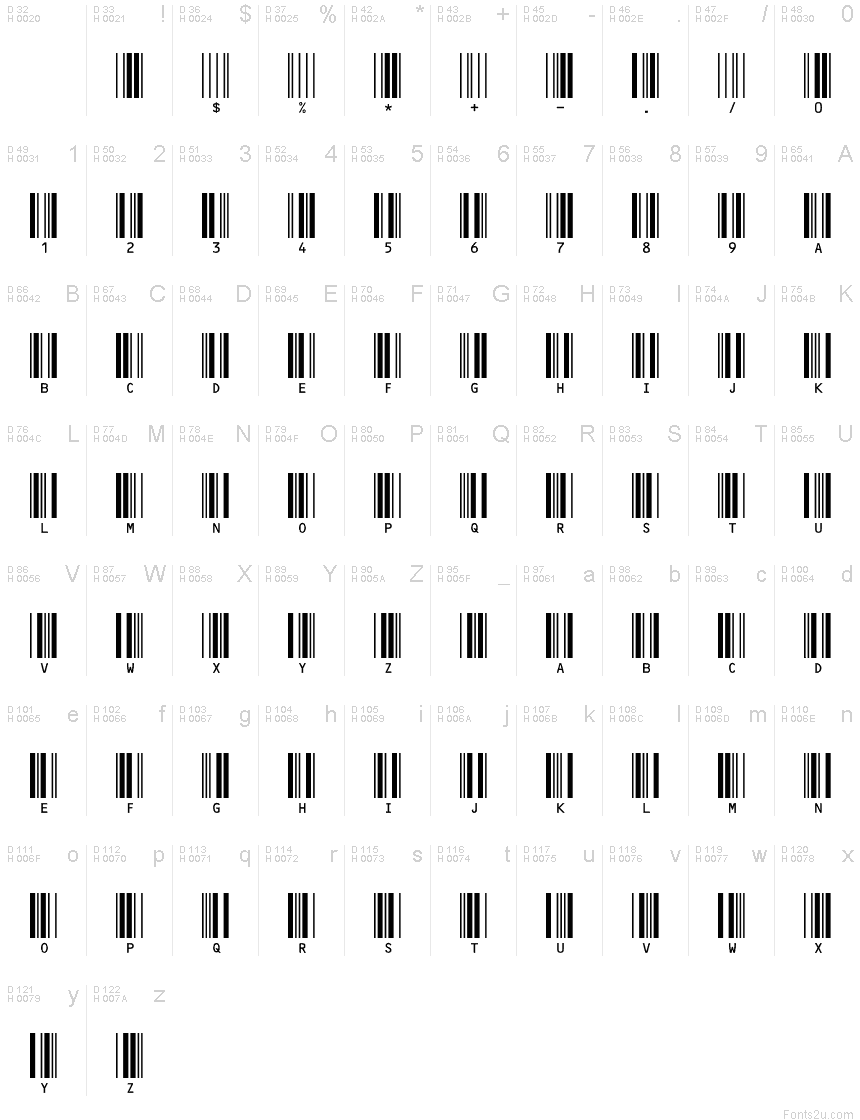
C39HrP36DlTt 字体
C39Hr 字体家族,包含 4 款字体
C39HrP36DlTt
Bear Rock Technologies 推出的 C39HrP36DlTt 是一款免费的条形码 Dingbat 字体,能为您的设计增添一种清晰、机器可读的质感。其紧凑的竖线条和均匀的节奏完美模拟了真实的产品编码,让您的设计瞬间呈现出工业化、可扫描且逼真的视觉效果。即使在小尺寸或低分辨率输出(从标签打印机到普通办公复印机)下,这些笔画依然能呈现出致密、浓郁的条纹效果。
在包装样机、产品标签、票据、杂志、UI 线框图或仓库标签上使用 C39HrP36DlTt,能立即传达出“真实”库存或门禁控制的既视感。这款免费字体在大字号下更能凸显其编码质感;建议将周围的补充信息搭配简单的无衬线字体,以确保条形码纹理保持视觉焦点,易于识别。